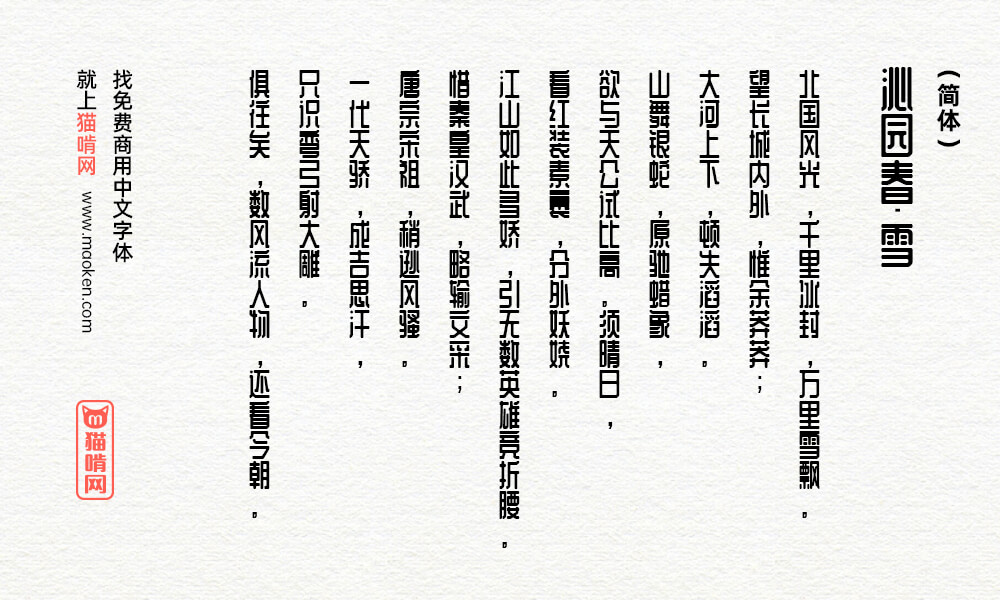
| 字体作者:郑庆科 (中国大陆) | 字体字重:1个 |
站酷庆科黄油体是一款字型创新、线条圆润的字体。笔划的每一个直角,都被处理成了半径为4pt的圆角。在设计中需遵循笔划简化但不省略,笔划角度尽量为垂直角度。字体部首的右下角均为45°缺角,提高了字体视觉中心,并有效的解决了一些字体因笔划交叉,字体阅读困难的毛病。
郑庆科黄油体字体是一款用于创意设计方面的字体,该字体紧凑,识别性强,端正大方,整体风格出色。 它的英文字体和数字的风格跟中文汉字的样式其实是两种不尽相同的风格,郑庆科黄油体的英文字母与数字采用了折叠式设计思路,让人看起来就像是长条的纸张折叠出来的效果!
郑庆科黄油体这款中文字体整体偏可爱的风格,特别适合当店招、banner、标志、等领域,设计效果十分出色!